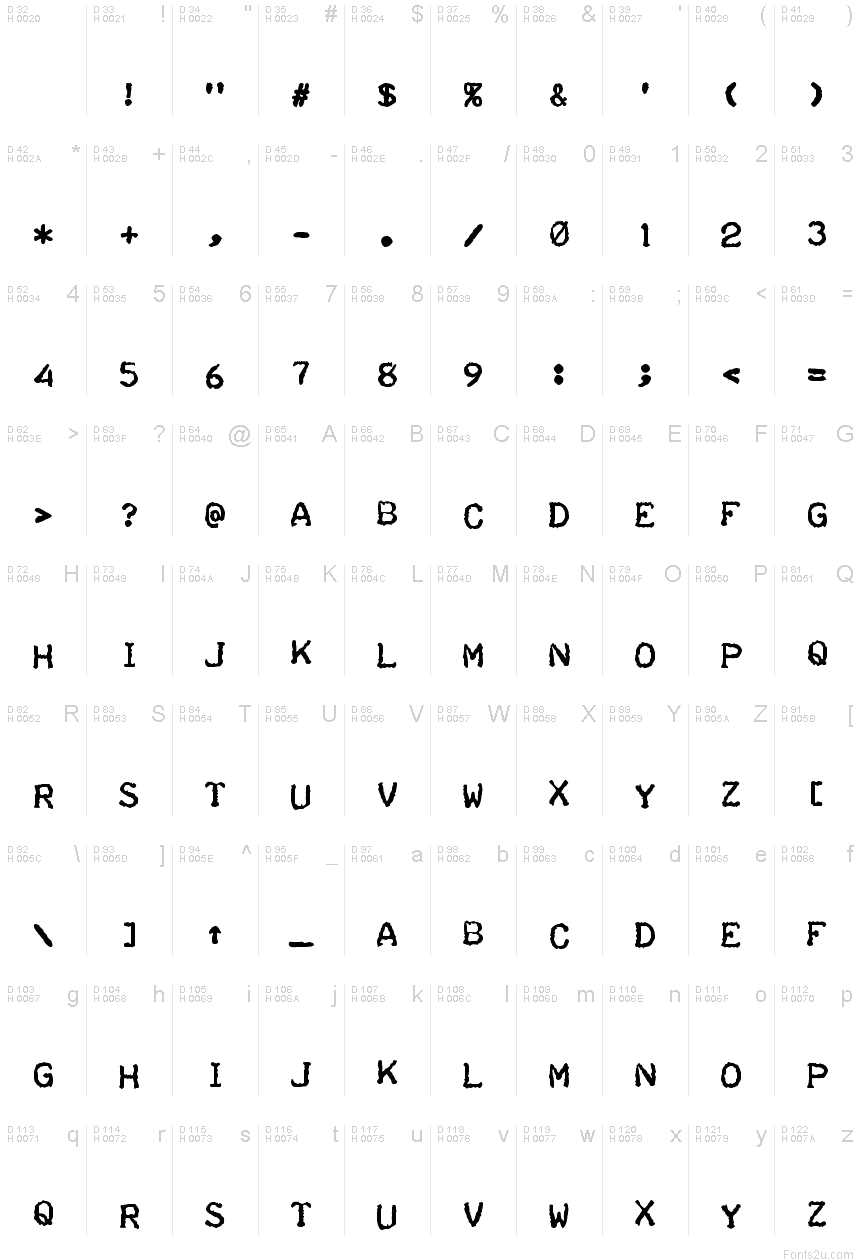
Teleprinter Bold Italic autorstwa Marka Zanziga to darmowy, zniekształcony krój ekranowy w stylu maszyny do pisania z charakterystycznym, "zalanym tuszem" klimatem. Wielkie litery wyglądają na tępe i zniszczone, z poszarpanymi krawędziami, nabrzmiałymi łączeniami i delikatnymi zaciekami, dzięki czemu sprawiają wrażenie przybijanych pieczątką, rozmazanych i nieco nieokiełznanych.
Świetnie sprawdza się wszędzie tam, gdzie chcesz uzyskać efekt "zepsutej maszyny" w tytułach plakatów, okładkach zinów, ulotkach horrorów, okładkach albumów czy krótkich hasłach brandingowych. Jako darmowy font nadaje się również do plansz tytułowych, otwarć rozdziałów i dużych inicjałów, ponieważ masywne sylwetki liter zachowują graficzny charakter, a ich chwiejność sprawia, że pismo nie wygląda zbyt schludnie ani mechanicznie.